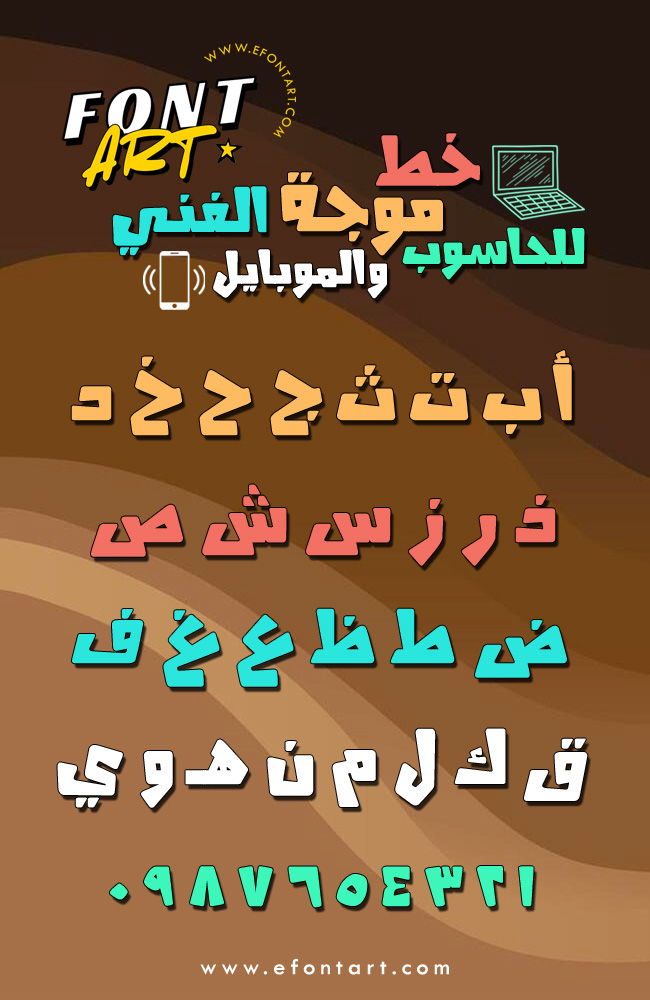
خط موجة الفني للحاسوب والموبايل .. خط عربي فني عريض ، يصلح للموبايل وأجهزة البي سي والتابلت ، يمتاز الخط بشكله الفريد حيث يمكن استخدامه في العناوين العريضة والدعاية والإعلان ، كما أنه يعمل على كافة برامج الأوفيس وبرامج التصميم المتنوعة ، وهو متاح للتحميل الآن .
خط موجة الفني للحاسوب والموبايل